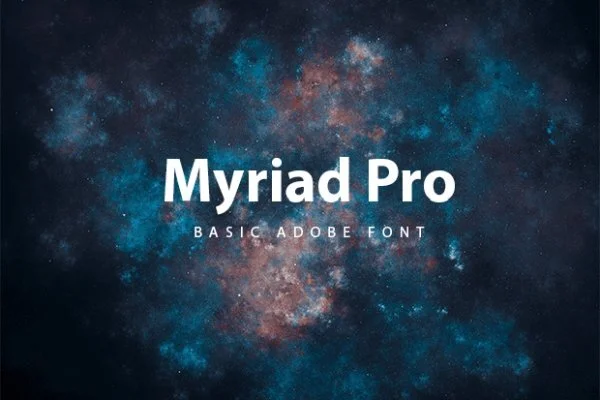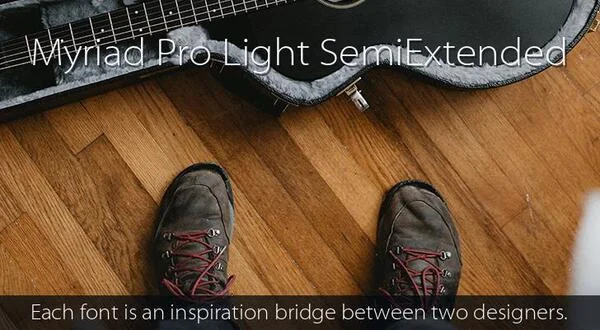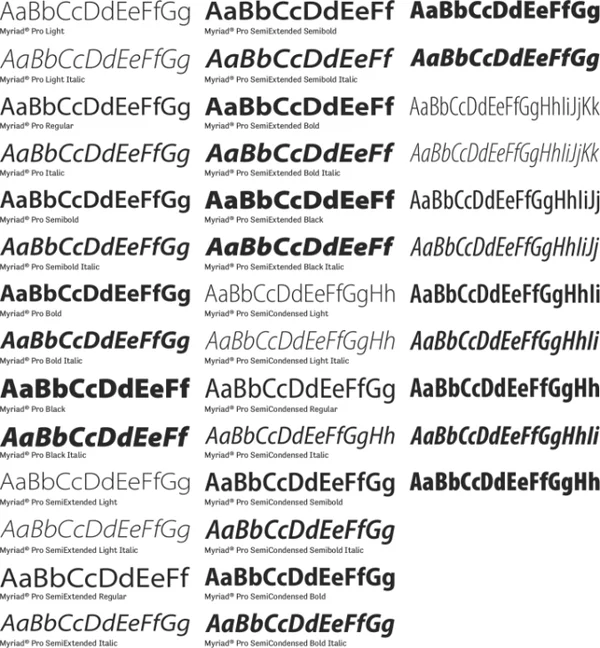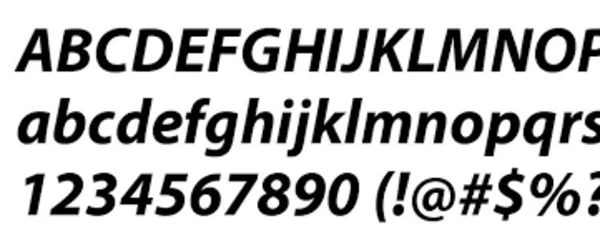
Font Myriad pro hẳn không còn xa lạ gì với các designer khi nó được sử dụng cho nhiều mục đích thiết kế khác nhau. 2 nhà thiết kế chữ Robert Slimbach và Carol Twombly đã cùng hợp tác để thiết kế font chữ này cho Adobe, vì vậy font chữ này rất tiện lợi cho những người sử dụng Adobe Illustrator, Photoshop, IDesign,... Bài viết này của Printgo sẽ gửi đến các bạn link tải font Myriad Pro full ở cuối bài và giới thiệu sơ qua về font chữ này.
Font Myriad Pro là bộ font chữ được Adobe sản xuất và tích hợp trong các sản phẩm công nghệ nổi tiếng của mình như Adobe Illustrator, Photoshop, IDesign… Bộ font chữ này đã được Việt hoá do nhu cầu sử dụng ngày càng cao của các designer và để phục vụ cho mọi mục đích thiết kế của họ.
Điểm nổi bật nhất của font chữ này là các nhà thiết kế có thể tạo ra nhiều cấp độ, ví dụ sự thay đổi về chiều rộng có thể thay đổi đôi chút đặc điểm của chữ. Với font Myriad Pro, người dùng có thể tạo ra các kiểu tùy chỉnh khác nhau một cách linh hoạt dựa trên thiết kế hay biến thể.
Font Myriad Pro mang đến cảm hứng sáng tạo cho nhiều người nên nó có rất nhiều biến thể, trong đó nổi bật nhất là 2 biến thể Opentype và Myriad Web. Bộ font Myriad Pro full gồm 15 kiểu từ Light Condensed tới Black SemiExtended và đa số đã được Việt hoá. Các bạn có thể tìm thấy link down font Myriad Pro ở cuối bài viết này.
Font chữ này thường được sử dụng để thiết kế: